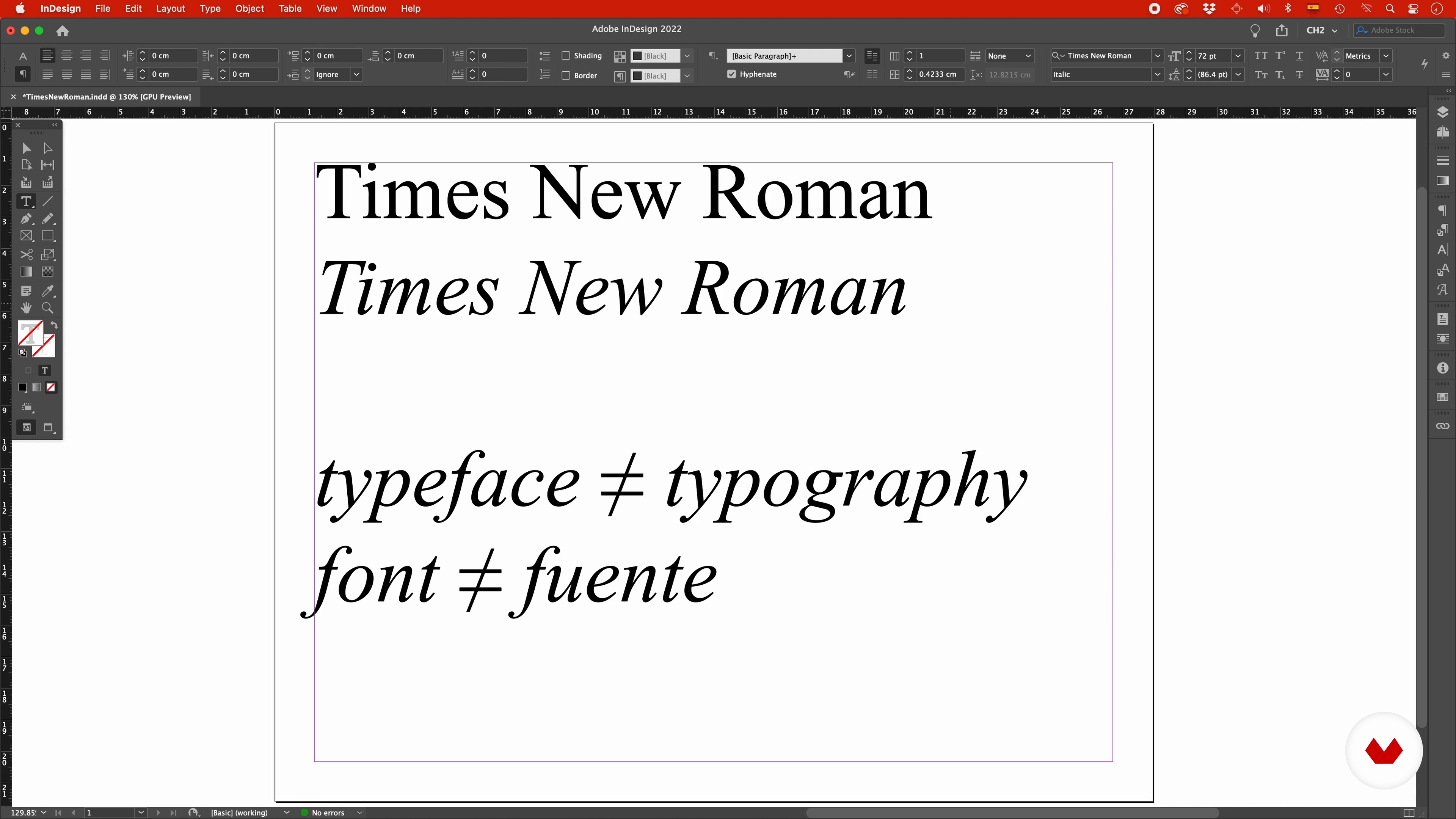
Basisdefinities
Over de videoles: Basisdefinities
Samenvatting
“Handschrift, kalligrafie, typografie en belettering hebben allemaal te maken met het gebruik van letters, maar niet op dezelfde manier. Ontdek samen met mij het verschil tussen al deze in deze les.”
In deze videoles behandelt Cristóbal Henestrosa het onderwerp: Basisdefinities, dat deel uitmaakt van de online cursus van Domestika: Ontwerp typografie en digitaliseer je eigen letters. Zet je handgemaakte letters om in een unieke, digitale typografie die persoonlijkheid toevoegt aan alles wat je schrijft.
Gedeeltelijke transcriptie van de video
“Basisdefinities Typografie is schrijven met geprefabriceerde letters omdat ze al bestaan, zitten ze in de computer en u activeert deze wanneer u op een toets drukt. In plaats daarvan bestaat handschrift niet maar totdat je een instrument oppakt en ermee schrijft. Laten we zeggen dat het in realtime bestaat. Er zit een paradigma in je hoofd van hoe het eruit zou moeten zien, maar je weet pas hoe het afloopt als je het weet. Typografie biedt daarom gebruiks- en reproductiemogelijkheden dat de handleiding brief niet heeft en daarom is het in het belang dat uw handschrift typografie worden. Ik ...”